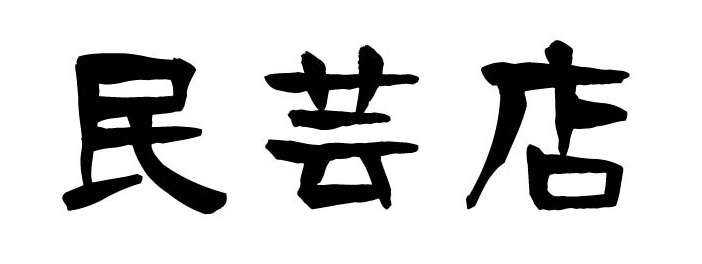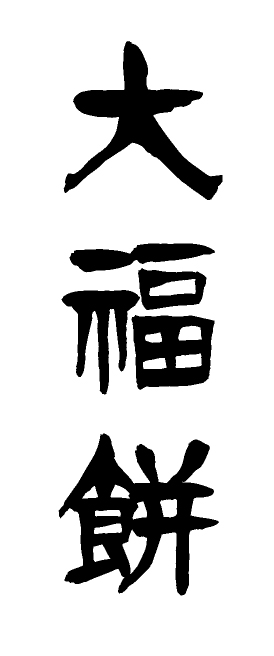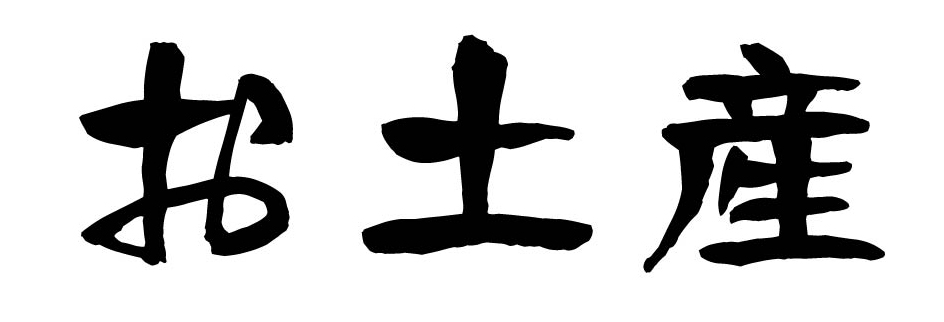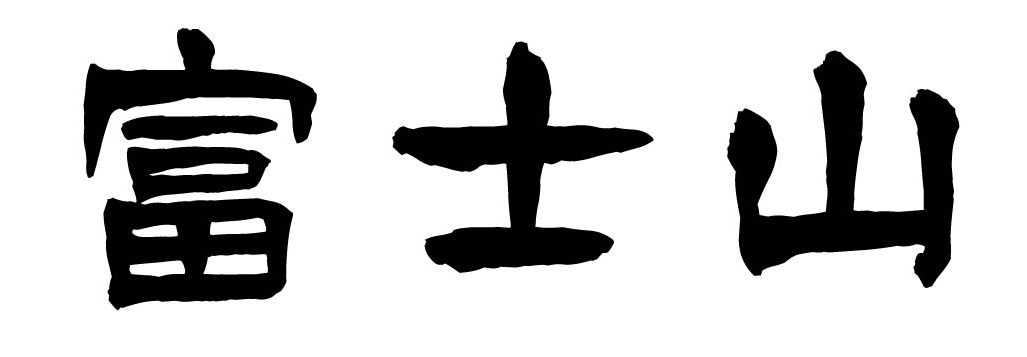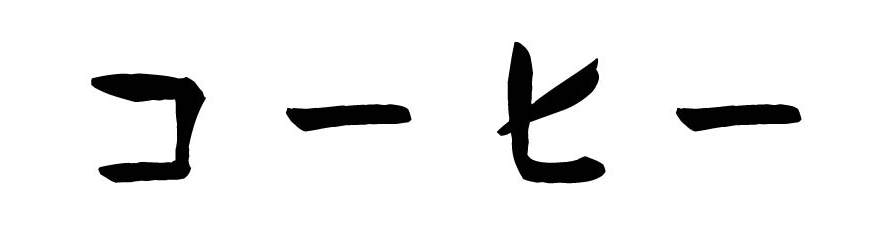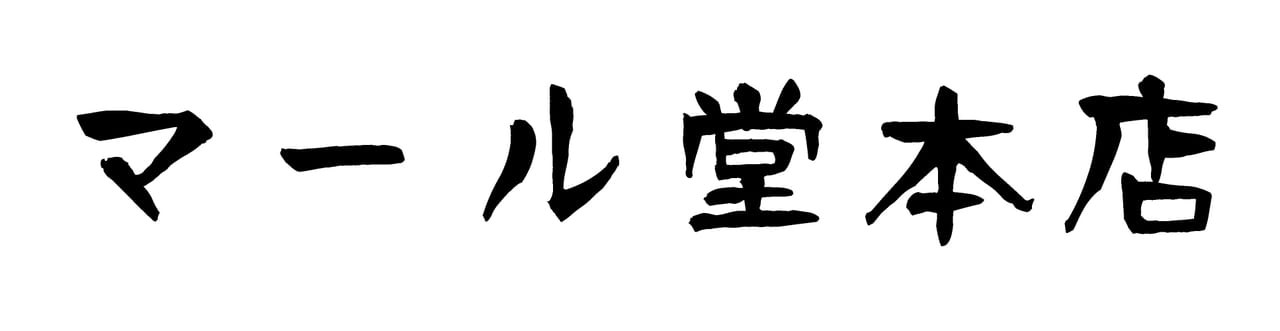
デザイン筆文字フォント 石隷 (ダウンロード版)
【書:川原石光】
このフォントは弊社書籍『デザイン筆文字シリーズ3石隷』(川原石光 著)を、株式会社武蔵システムがフォント化したものです。毛筆の落ち着いた筆致が特徴的なフォントです。ポスターやメニュー、同人誌の表紙など、あらゆる場面で大活躍。フォントフォーマットは、TrueTypeとOpenTypeです。1ライセンスに両方含まれます。印刷物への使用など一般的な商業利用は追加料金なしで可能です。詳細については、上記リンク「使用許諾範囲」を、ご購入前に必ずご確認ください。
・「、」や「。」促音の「っ」や「ッ」などは文字組を考慮して文字位置を調整しています。一部の文字は仮想ボディをはみ出しているため、TrueTypeフォントを使って縦書きした場合、左右に仮想ボディをはみ出している部分が表示されないことがあります。その場合はOpenTypeフォントを使ってください。